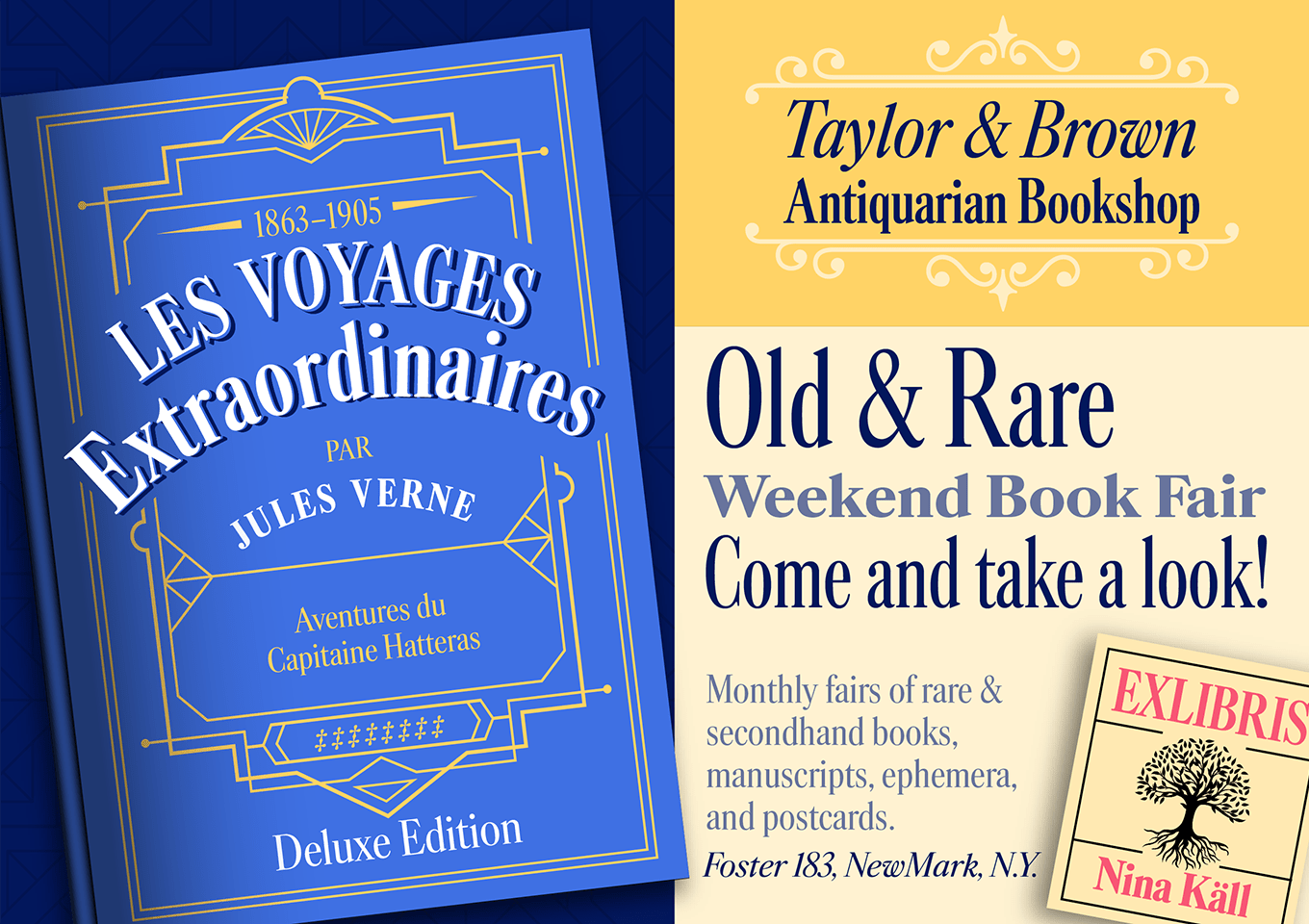
Caslonの活字をベースにやや現代的に整理された小見出し用のトランジショナル・ローマン体です。エレメントの先端が溶けたような丸みのあるニュアンスを持ち、太いウエイトになるほどその特徴が顕著に表れます。あたたかみがありながらも堅牢なデザインで、本文から見出しまで幅広くお使いいただけます。通常の字幅に加え、見出し利用に最適な長体のCondensedとCompressedも用意されています。